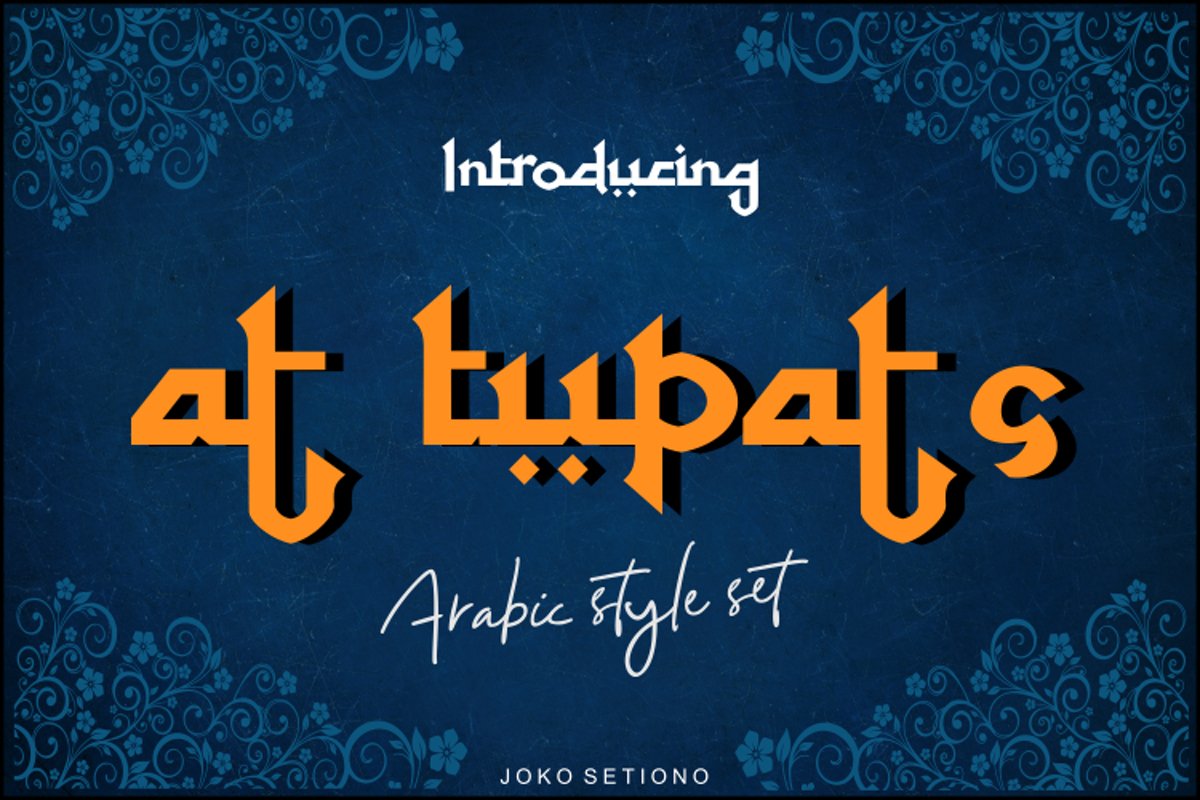
at tupats- arabic stalys set
at tupats
yang kami beri nama "at tupats".
at tupats adalah font gaya arab dengan gaya yang sangat indah dan elegan.
terinspirasi oleh kaligrafi kuno yang sangat indah dan tepat.
Fitur ligatur, gaya stylystic, dan konteks kontekstual pada font ini akan membuat tulisan Anda mirip dengan kaligrafi Arab.
sangat cocok untuk menulis gaya timur tengah. restoran, majalah, suvenir, web, dan banyak proyek bertema ramadhan.